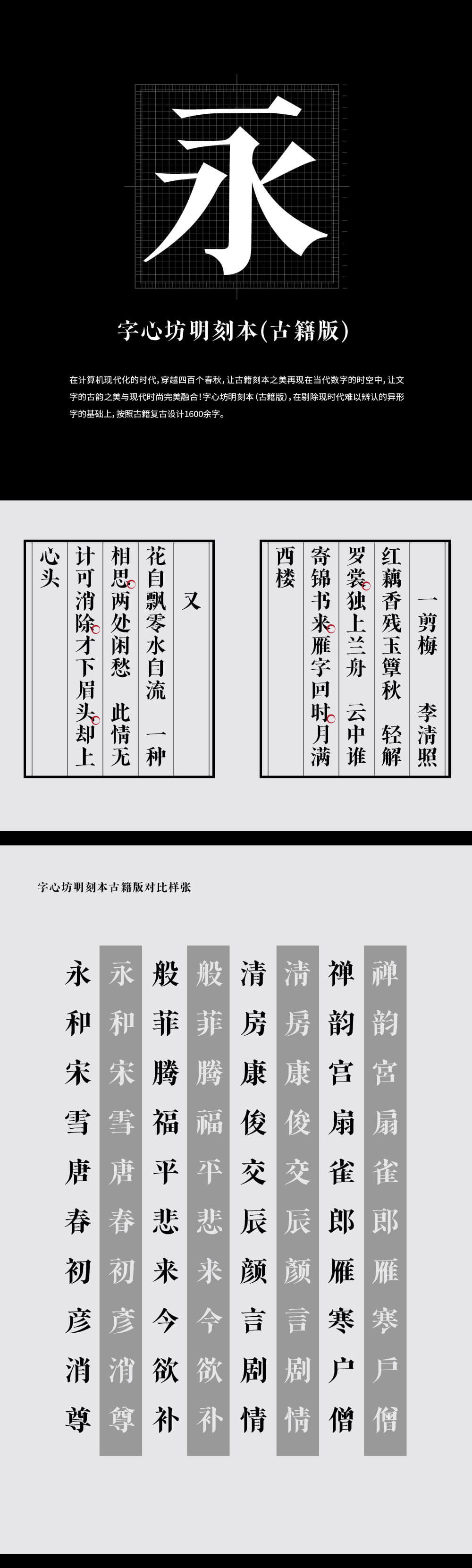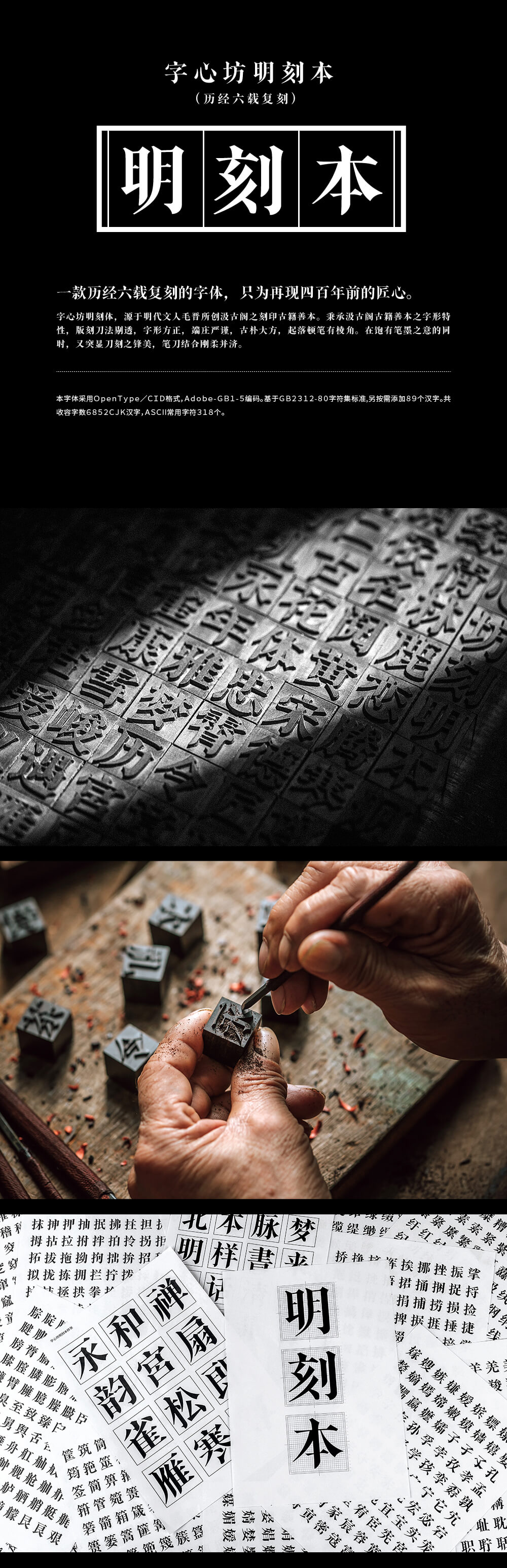
字心坊明刻体,源于明代常熟文人毛晋创办的汲古阁的刻印古籍善本。秉承汲古阁古籍善本之字形特性,版刻刀法剔透,字形方正,端庄严谨,古朴大方,起落顿笔有棱角。在饱有笔墨之意的同时,又突显刀刻之锋美,笔刀结合刚柔并济。
在秉承笔形间创新,结合当代设计视觉环境,融入现代审美,适用场景更多元,笔画造型清晰锐利,删繁取简,笔锋凌厉,速度感强,粗细对比强烈,重现刀刻古韵之美。在计算机现代化的时代,穿越四百个春秋,让古籍刻本之美再现在当代数字的时空中,让文字的古韵之美与现代时尚完美融合!
一款历经六载复刻的字体,只为再现四百年前的匠心。
从2013年6月,至2019年9月,历经6年时间,共计7个设计师;
翻阅古籍几万余字,经过近百个组样稿的修改,最终确认笔画细节的定型设计;
历经5次整体重新设计和修正,共设计3万余字样,废除近2万余废字字样,最终定稿8000余字样。
该字体分为字心坊明刻本和字心坊明刻本(古籍版)两个版本。